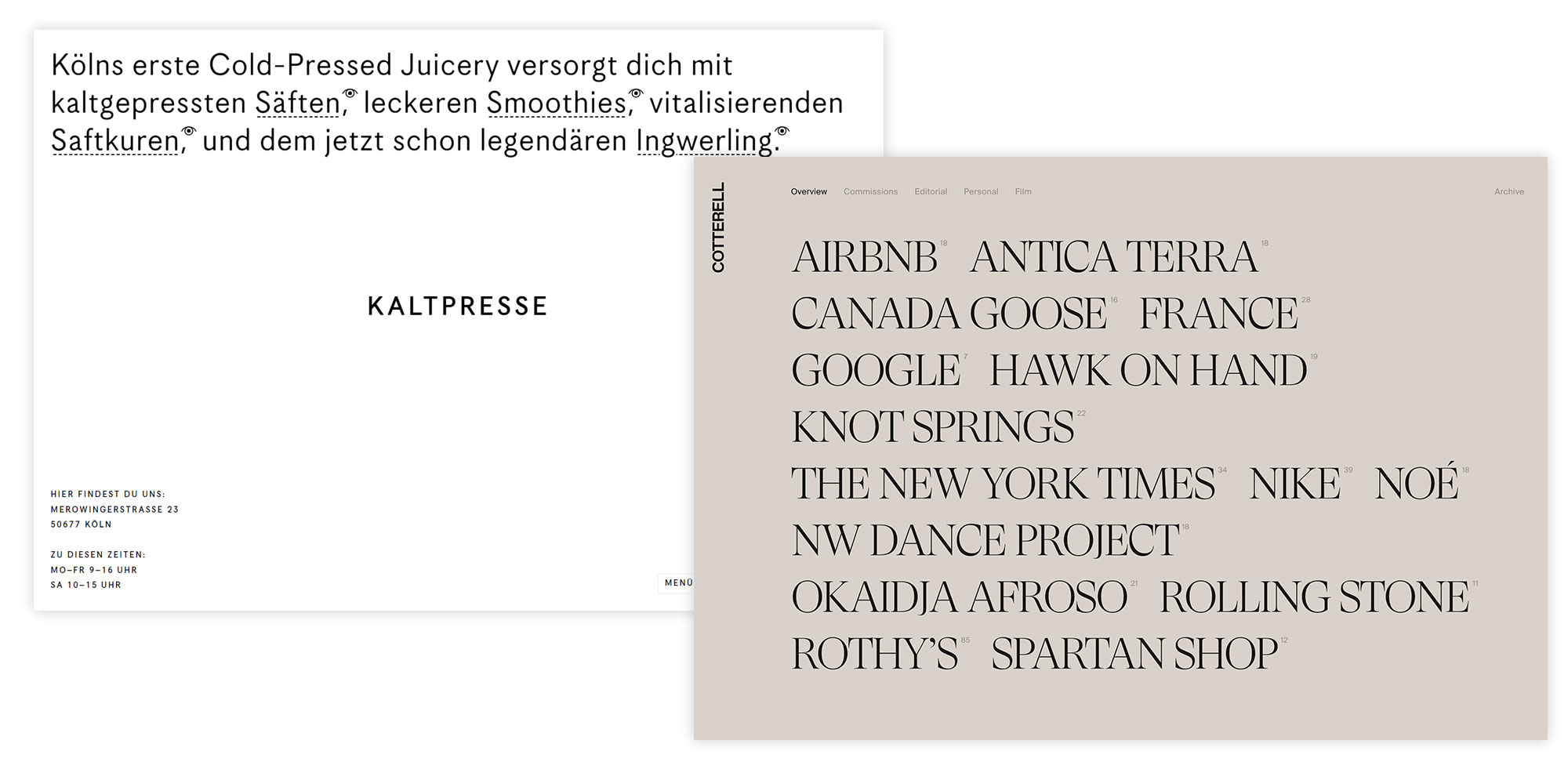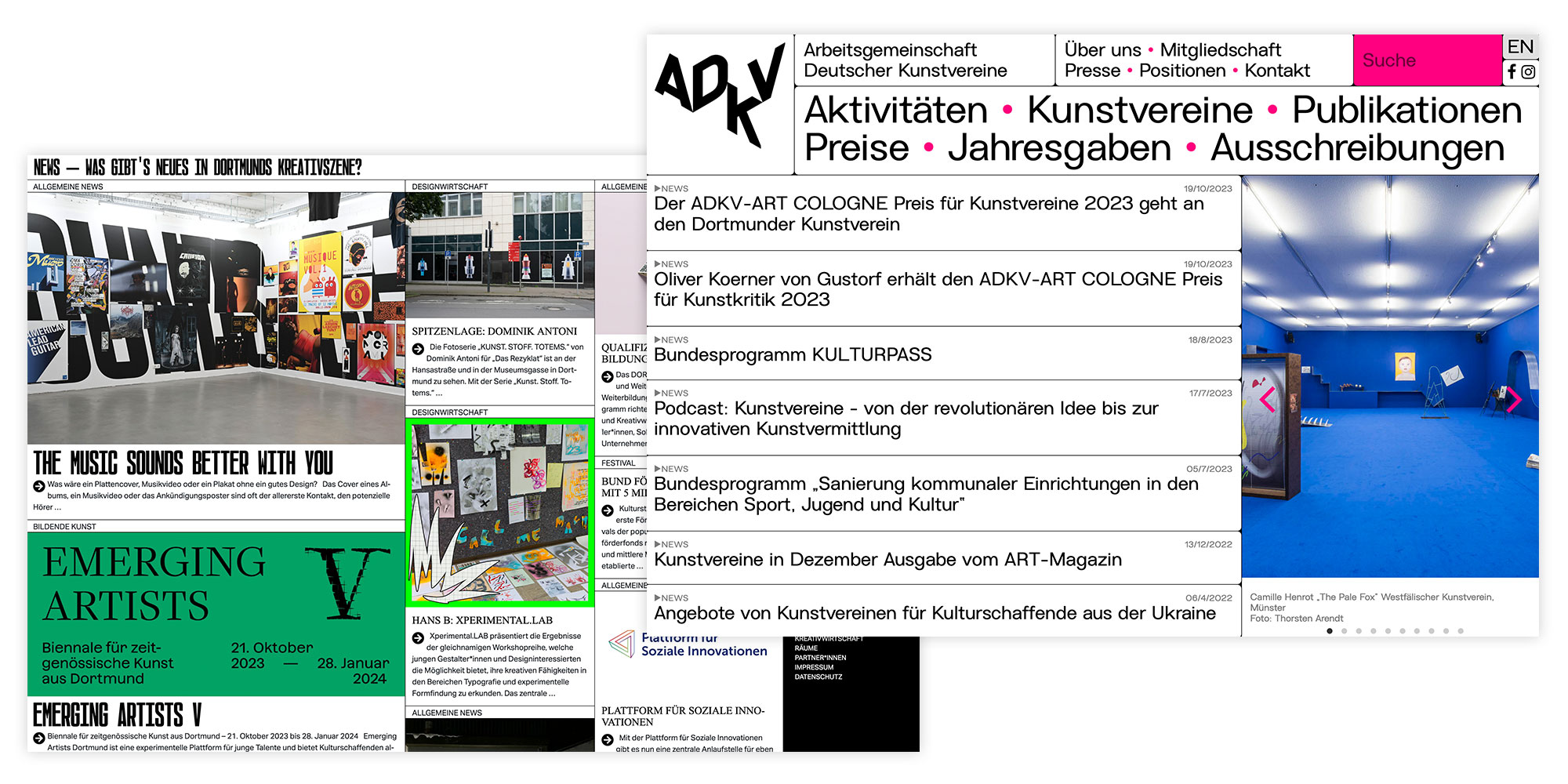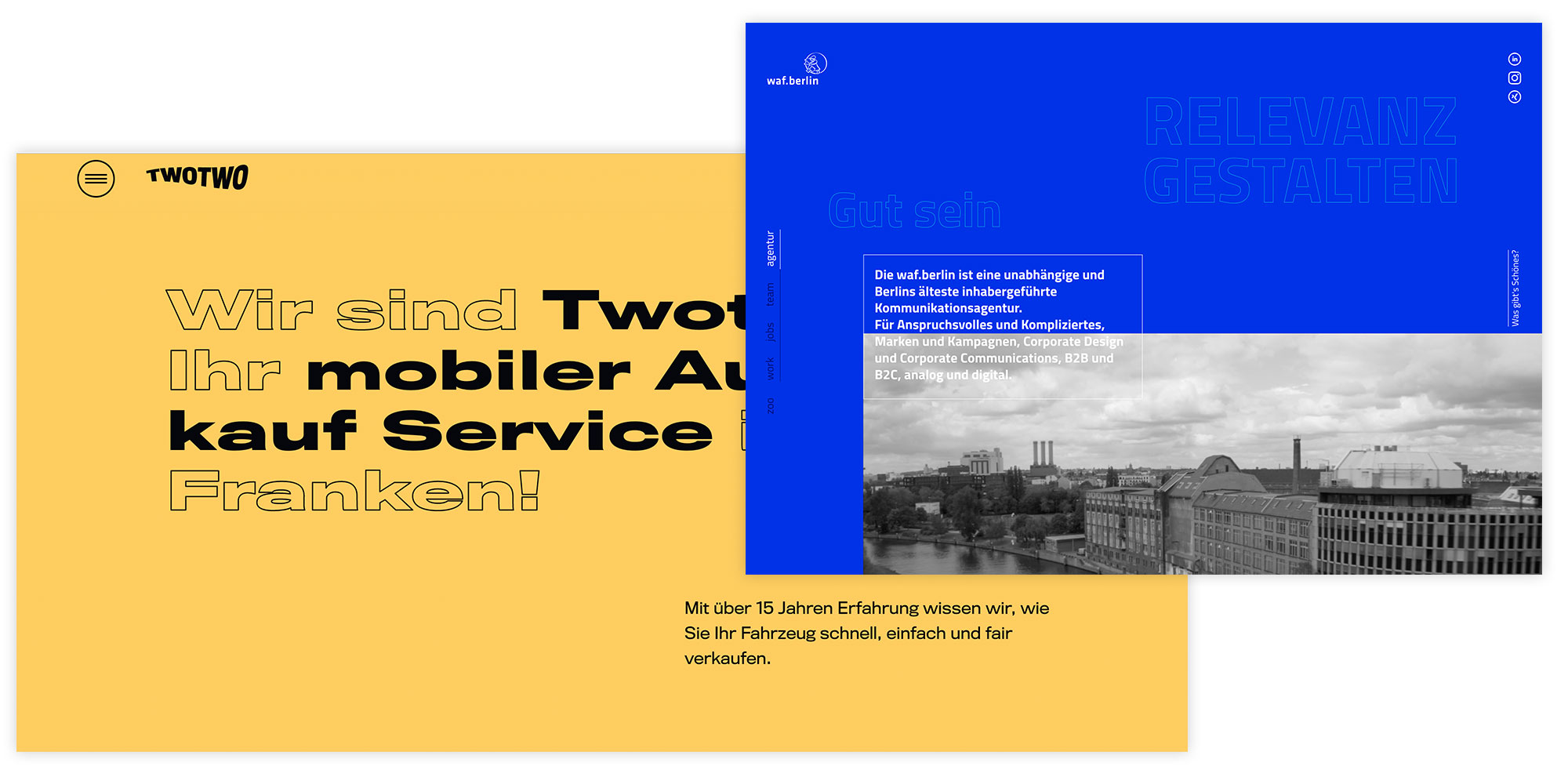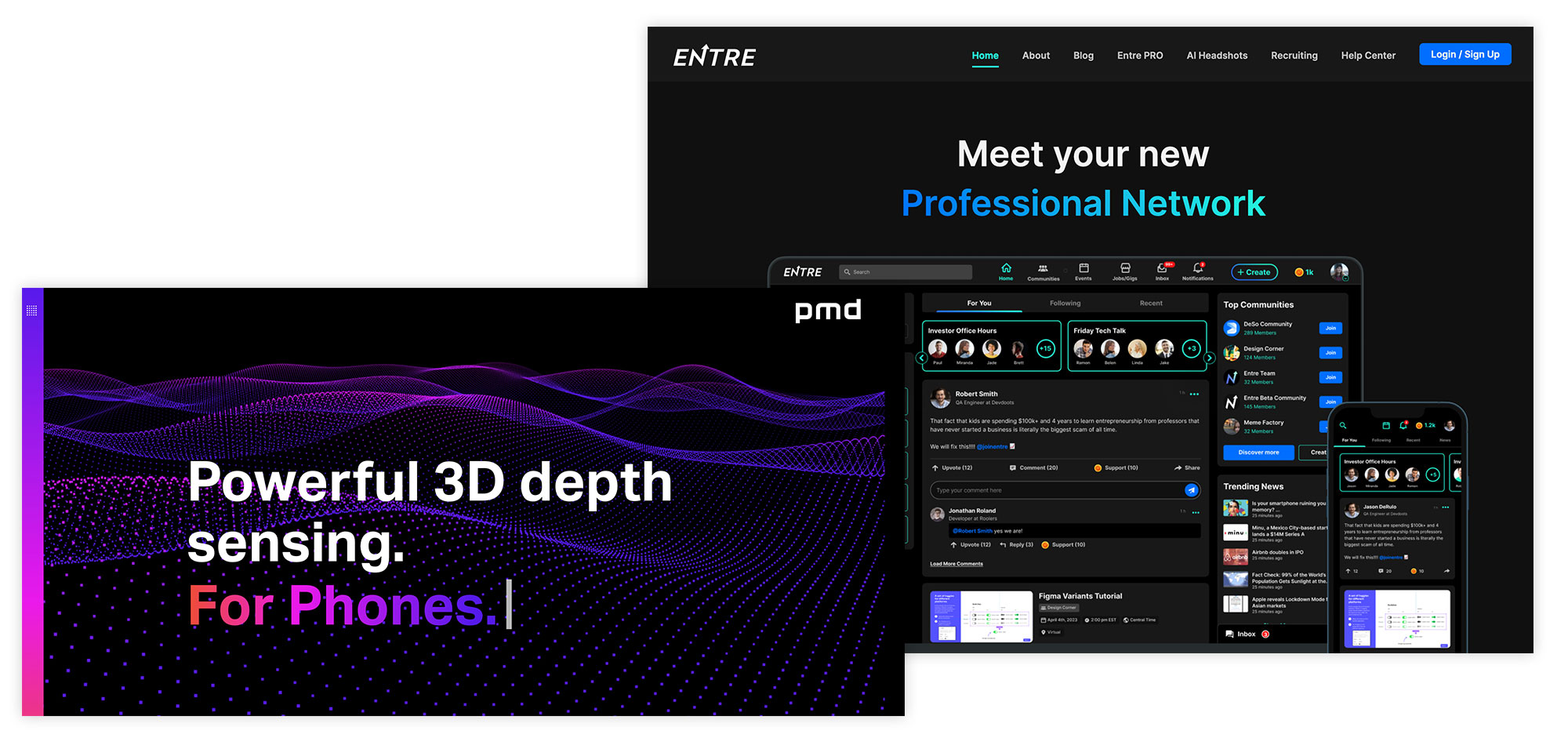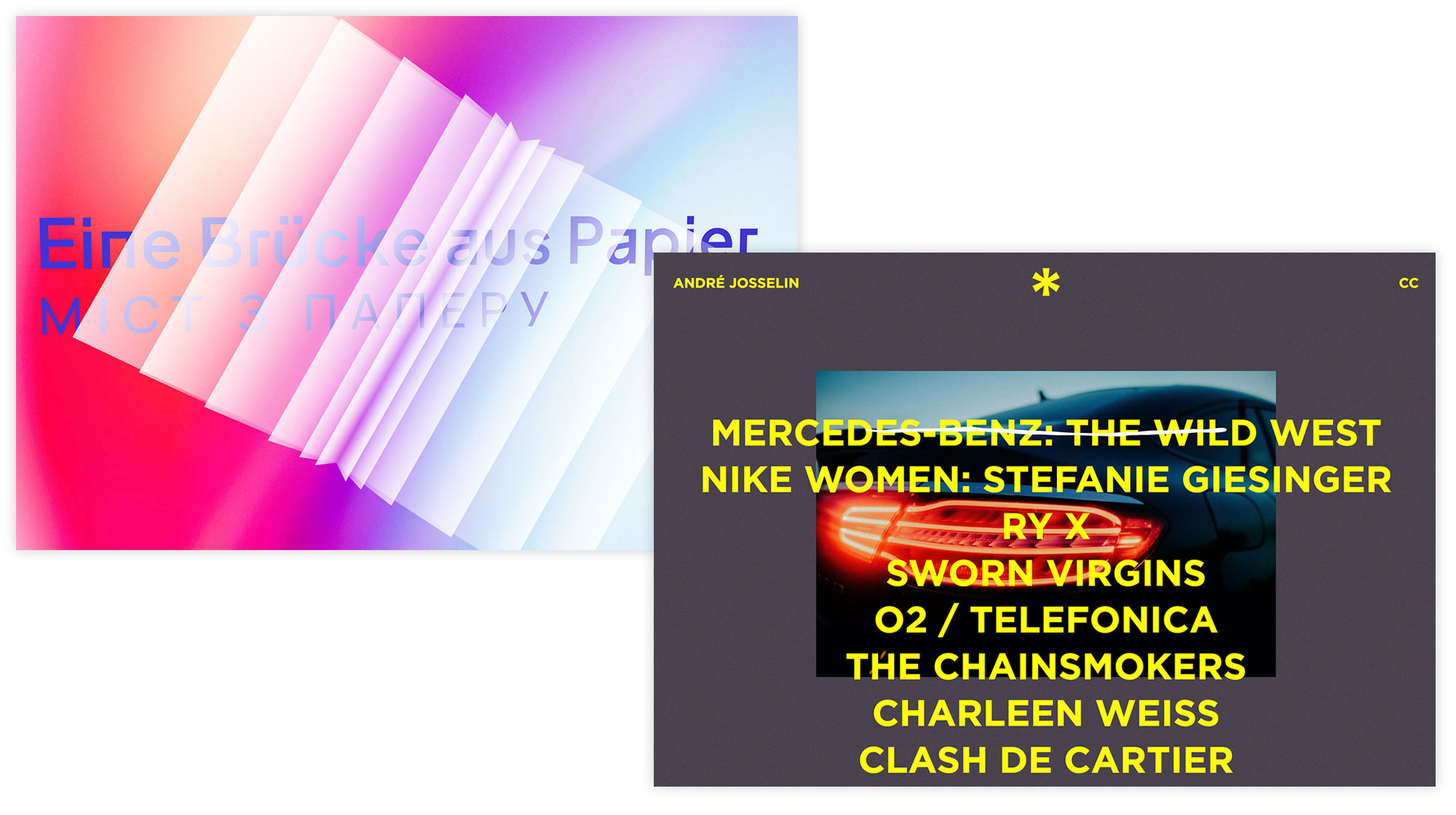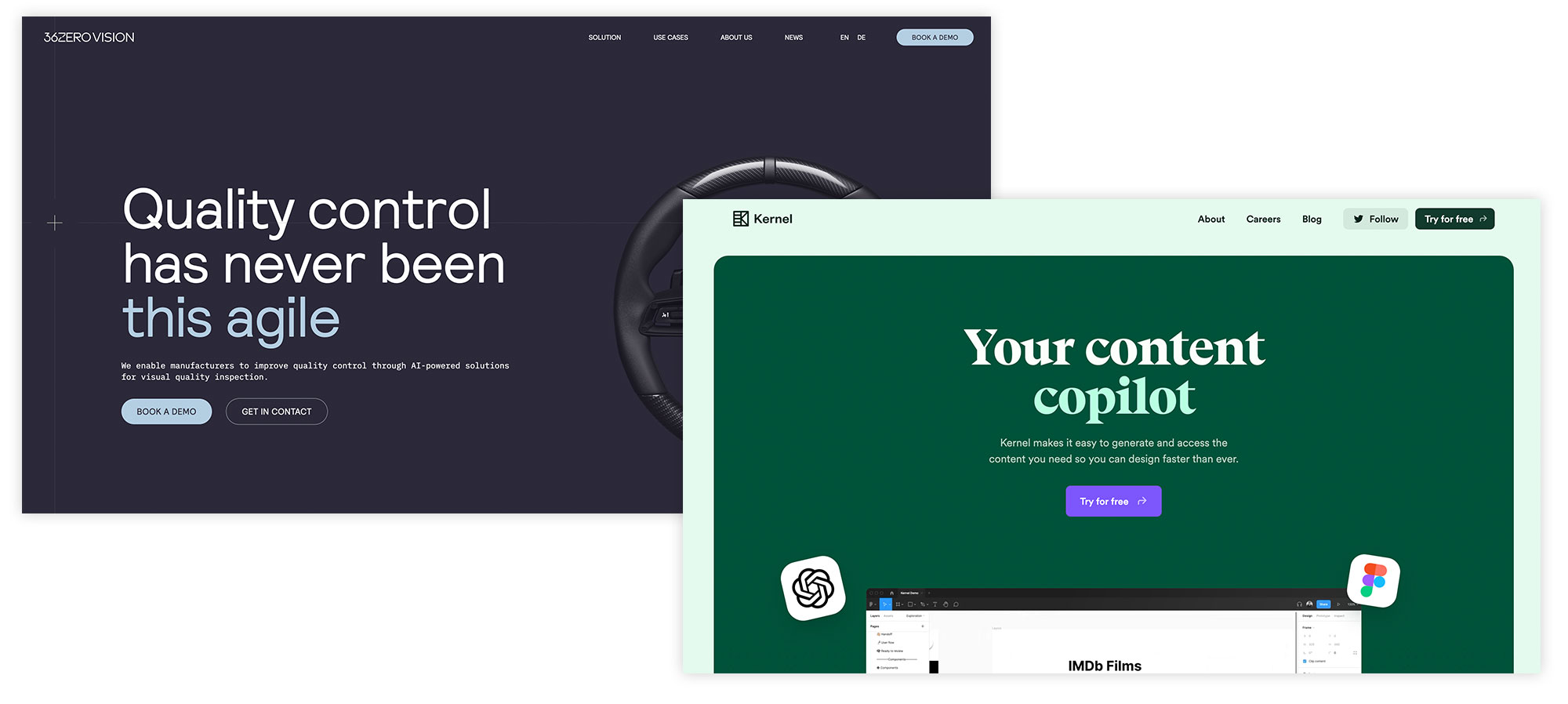
Die Top-Typographie-Trends im Überblick
Welche Top-Trends du für die Typographie im Webdesign kennen solltest und wie du sie nutzen kannst, erfährst du in diesem Artikel.
Wenn du gerade dabei bist, eine Website ansprechend zu gestalten, wirst du sicherlich auch den ein oder anderen Text verwenden. Dafür solltest du dich zunächst mit den Möglichkeiten der modernen Typographie auseinandersetzen. Denn:
Immer wieder gibt es neue Trends, die sich in zahlreichen Bereichen durchsetzen und die Gunst der Nutzer auf sich ziehen möchten. Doch welche Trends zeichnen sich für die Zukunft ab und wie kannst du diese nutzen, um deine Texte wirkungsvoll zu gestalten? Das liest du in diesem Artikel.
Was ist Typographie im Webdesign?
Typographie im Webdesign umfasst die kreative und funktionale Gestaltung von Texten, um sowohl die Lesbarkeit als auch die visuelle Wirkung zu optimieren. Moderne Trends wie Fettschrift, farbige Texte oder zweifarbige Überschriften helfen dabei, wichtige Inhalte hervorzuheben und eine starke visuelle Präsenz zu schaffen. Mit gezieltem Einsatz dieser Trends kannst du nicht nur die Aufmerksamkeit deiner Leser gewinnen, sondern auch den Wiedererkennungswert deiner Website nachhaltig steigern.
Fette Texte
Du kennst sie vermutlich schon: fette Texte.
Tatsächlich ist es nach wie vor so, dass fett geschriebene Worte und Textzeilen die Aufmerksamkeit des Lesers auf sich ziehen. Bei der Fettschrift werden alle Buchstaben linear verstärkt. Der Effekt: Die Schrift wirkt auf den Leser klarer und deutlicher. Überschriften in Bold-Schrift können mit dem Auge schneller erfasst werden, außerdem erhöht sich die Lesbarkeit der Texte, die in Fettschrift dargestellt werden.
Für den Leser wird deutlich, dass einzelne Schlagworte, die fett markiert sind, bedeutend sind. Das ist vor allem für die User praktisch, die einen Text lieber überfliegen als ihn Wort für Wort zu lesen.
Fettschrift lenkt die Aufmerksamkeit der Leser und erhöht die Lesbarkeit durch klare und deutliche Buchstaben.
Brutalism
Brutal und somit Aufmerksamkeit erregend ist dieser Typographie-Trend, der sich in den nächsten Jahren vermutlich behaupten wird. Funktionalität steht vor Ästhetik, denn bei diesem Gestaltungstrend werden klare, harsche Formen dargestellt, die fast minimalistisch und roh anmuten.
Dekorative Elemente sucht man bei diesem Designstil vergeblich, denn Brutalismus setzt auf klare Botschaften. Kontrastreich sind die Schriften, die im Brutalism gezeigt werden und sich so von anderen Texten abheben.
Brutalismus setzt auf rohe, minimalistische Formen und klare Botschaften – eine Typographie, die auffällt.
Highlight-Texte
Damit du dich mit deiner Seite von der Konkurrenz abhebst, muss deine Homepage so gestaltet sein, dass der Leser sich gerne näher zu deinen Produkten oder Dienstleistungen informiert. Er möchte hochwertige Texte lesen, die so gestaltet sind, dass wichtige Informationen schnell auffindbar sind. Highlight-Texte setzen genau darauf und ermöglichen so, das Interesse der Leser zu wecken und die Lesbarkeit zu optimieren. Helle Farben, die Textpassagen hervorheben, Call-to-Actions, die in bunten Farben zur Reaktion aufrufen oder auch Videos und Bilder können als gestalterisches Element eingesetzt werden.
Dabei solltest du allerdings darauf achten, dass die Highlight-Passagen nicht zu lang sind. Hebe nur wichtige Aussagen, Schlagwörter oder Links hervor. Andernfalls kann sich der Leser schnell überfordert fühlen.
Farbige Texte
Schwarz-weiß war gestern: Wer seine Leser heute beeindrucken möchte, der setzt auf farbige Texte. Elegant wirken Websites mit schwarzem Hintergrund, während die Texte in leuchtend bunten Farben ins Auge stechen. Der starke Kontrast zwischen dem dunklen Hintergrund und den bunten Buchstaben weckt das Interesse der Leser und kann dafür sorgen, dass mehr Nutzer weiterlesen möchten.
Farbige Texte können mit anderen Gestaltungsmöglichkeiten verbunden werden, um einen einzigartigen Auftritt zu garantieren. Bunte Serifenschriften auf dunklem Hintergrund können sich von der Typographie der Mitbewerber abheben und für ein hochwertiges Design sorgen.
Farben und Kontraste in der Typographie schaffen nicht nur Eleganz, sondern wecken auch die Aufmerksamkeit der Leser.
Gradients / Farbverläufe
Elegante, kaum sichtbare Farbverläufe sind im modernen Webdesign weiterhin beliebt – und werden es bleiben. Dabei zeigt sich, dass insbesonders helle Farben, häufig auch Pastellfarben, beliebt sind. Durch die Auswahl der richtigen Farben erzielst du eine bessere Lesbarkeit für den jeweiligen Text und setzt die passende Stimmung.
Ebenfalls lassen sich mit dezenten Verläufen auch Zusammenhänge mit den Farben des Unternehmens erzielen – was wiederum die Verbindung zwischen Marke und Text stärkt. Klassische Farbverläufe kannst du für Schlagworte oder kurze Statements einsetzen.